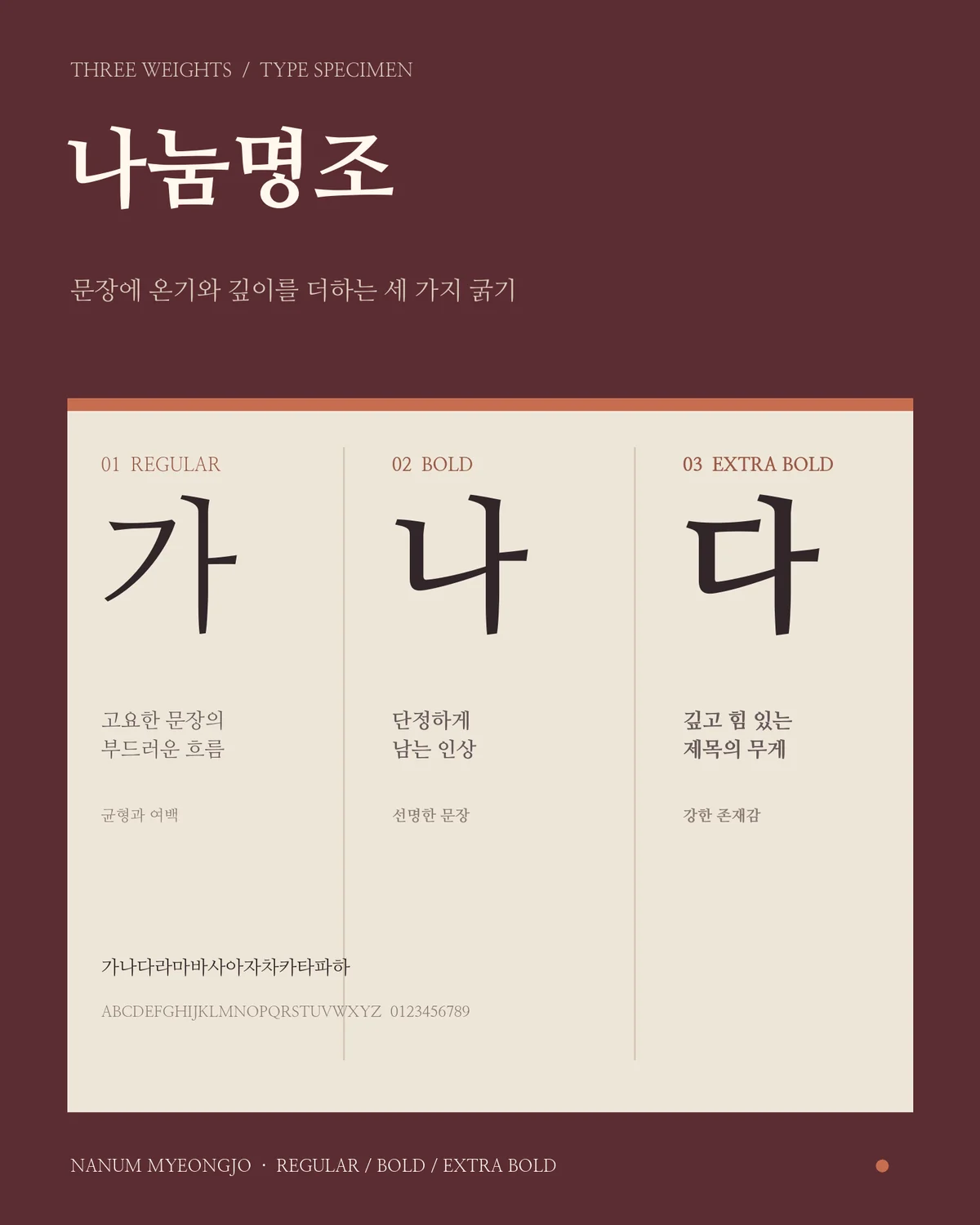
나눔명조 — 네이버에서 배포하는 무료 폰트입니다. 전통적인 명조의 뼈대에 현대적인 균형감을 더한 단정한 본문용 명조
2008년 한글날, 네이버가 나눔고딕과 함께 처음 공개한 나눔글꼴의 바탕 계열입니다. 나눔고딕을 산돌커뮤니케이션이 만든 것과 달리 이쪽은 폰트릭스가 제작했습니다.
구글폰트의 영문 소개는 이 서체를 따뜻한 감촉을 지닌 현대적인 세리프이며 화면에서 쓰도록 힌팅이 잘 되어 있다고 설명합니다. 특정한 옛 활자를 되살린 것은 아니고, 화면과 종이 양쪽에서 읽히는 본문용 명조를 새로 만든 쪽에 가깝습니다.
굵기는 2008년 Regular와 Bold로 시작해 이듬해 ExtraBold가 더해져 세 가지입니다. 나눔고딕과 마찬가지로 2010년부터 오픈 폰트 라이선스로 풀려 수정과 재배포가 자유롭습니다. 긴 본문과 출판물, 인용문에 두루 맞고 화면 본문에도 무리가 없습니다. 다만 가장 굵은 쪽이 ExtraBold라 아주 강한 인상의 제목을 만들기에는 힘이 모자랍니다.